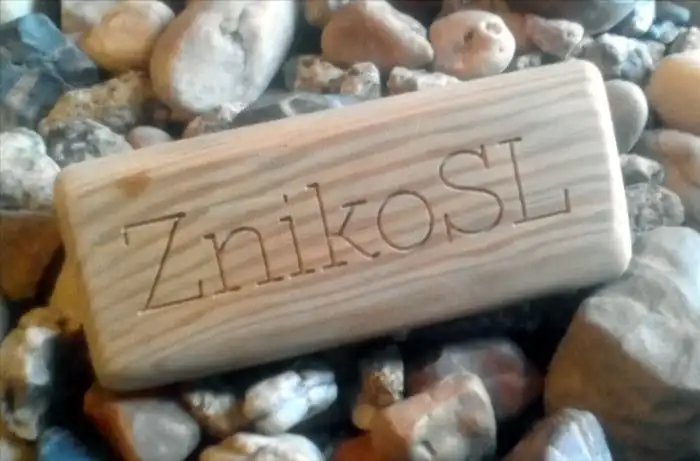
ZnikoSL Serif Font – Download Grátis
ZnikoSL Serif é uma fonte romana inspirada na arte gráfica italiana dos anos 40 e 50. Este tipo de letra exala elegância, com linhas limpas e claras que se adequam perfeitamente para fins como cartazes, headlines e textos longos. Foi criado pela glukfonts. ZnikoSL tem um visual minimalista que atende à estética da moda, design interno, publicidade e criação de sites. Escolha esta fonte para dar o toque final ao seu próximo projeto, seja ele impresso ou digital.